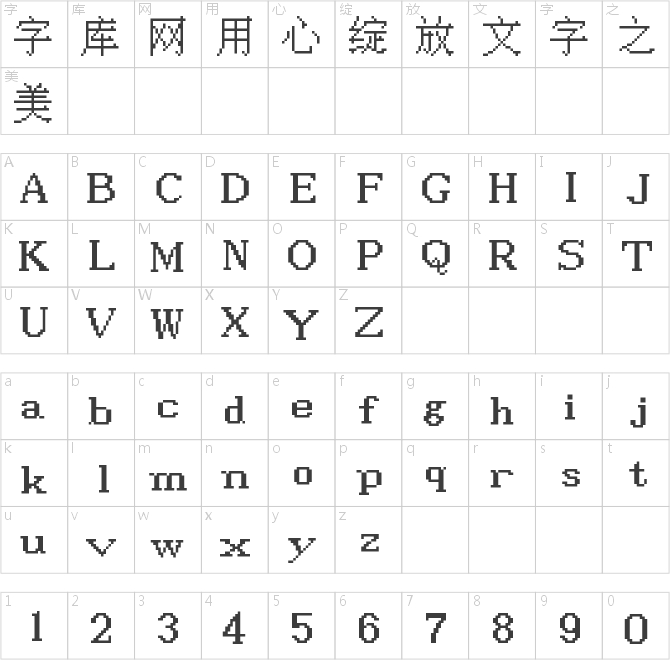
像素
字體介紹
中文像素字體是一款風(fēng)格比較特別的字體,這是一個(gè)像素中文字體,里面具有6000多個(gè)常用字 。特別適合復(fù)古游戲的制作和設(shè)計(jì),讓人好像回到了80年代那個(gè)紅白游戲機(jī)的年代。 這款字體是使用HZK16字模制作。而HZK16遵循的是GNU通用公共許可證。